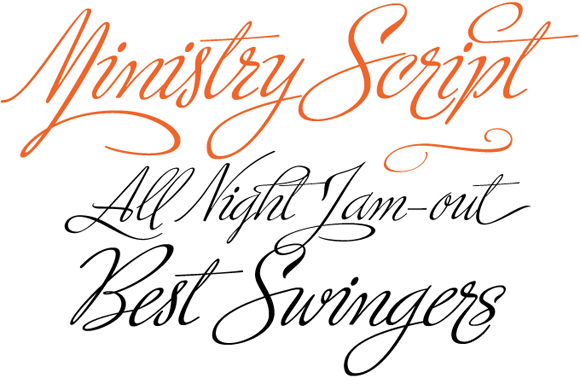
El tipógrafo argentino Alejandro Paul de Sudtipos, nos sorprende con su nueva creación tipográfica, una auténtica obra de ingeniería tipográfica que utiliza las nuevas funcionalidades que el formato Open Type nos brinda.